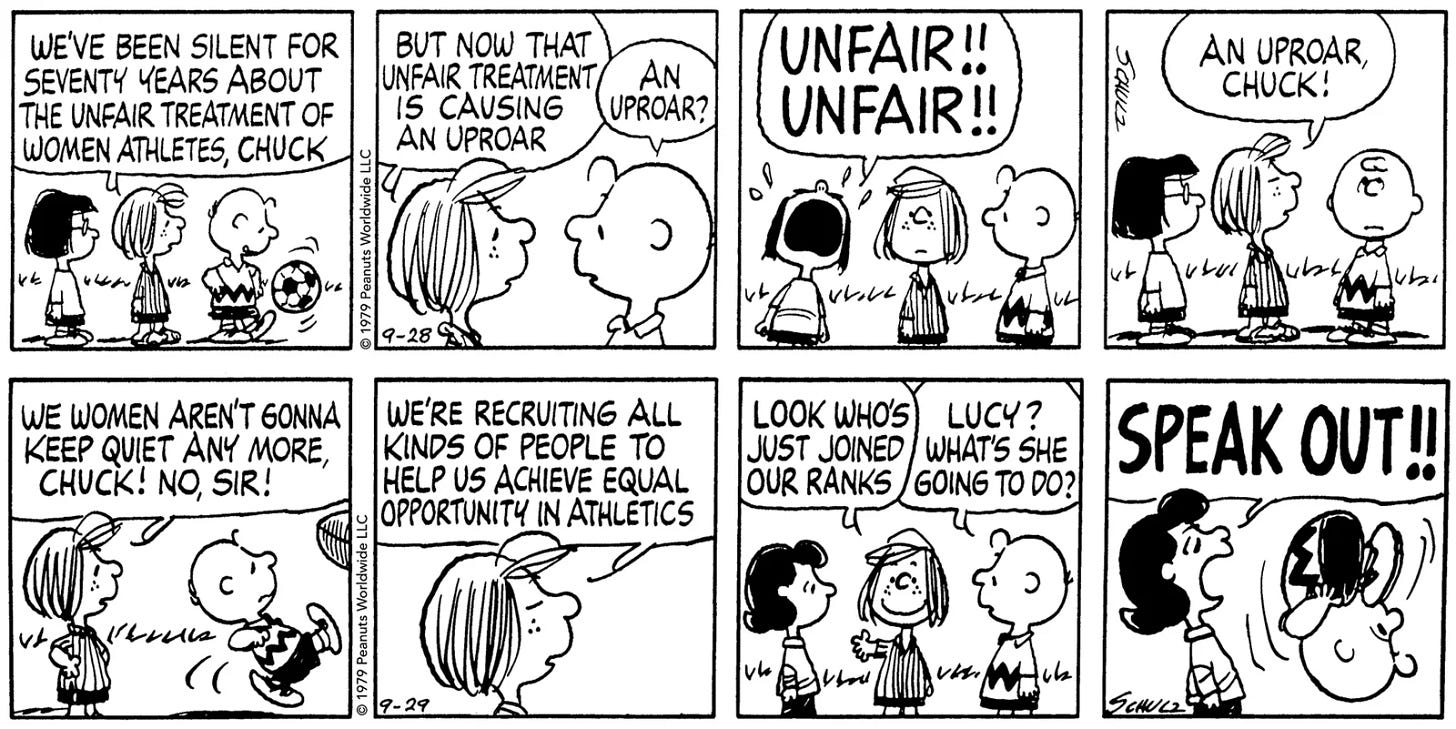
Tipo Aquilo #82 – Ziraldo e as letras dos quadrinhos
Analisando letras de quadrinhos e das artes de Ziraldo
Enquanto eu escrevo esse texto, há poucas horas, foi para as estrelas um dos mais ilustres cidadãos de Caratinga, MG. Aos 91 anos, Ziraldo faleceu em sua residência, deixando um legado de dezenas de personagens desenhados em milhares de quadrinhos, charges e cartuns. Eu sou da geração que conheceu a obra gráfica dele pelo Menino Maluquinho, sua peculiar panela na cabeça e sua turma que andava por jornais, gibis e chegou também aos cinemas. Mais ou menos na mesma época, conheci também o lado editorial de Ziraldo durante a breve existência da Bundas, uma sátira mensal da revista Caras criada para publicar entrevistas, artigos e charges que ilustravam o cotidiano social e político de um Brasil que deixara de ser uma ditadura de malditos milicos há pouco mais de 10 anos.
Como instrumento de crítica sócio-política pública, a Bundas não foi uma novidade na vida de Ziraldo; nos anos 1960, após passar por vários jornais de renome como cartunista, ele fundou “O Pasquim” com outros ilustradores da época, fazendo frente à gradual deterioração da democracia brasileira antes e após o golpe de 31 de março 1º de abril de 1964. O humor debochado era uma marca de Ziraldo, algo tão facilmente reconhecível quanto os traços de seus personagens e as letras espessas e cheias de contraste que escrevia para representar falas e outros elementos textuais. Aliás, é falando brevemente da história das letras usadas em quadrinhos que o Tipo Aquilo presta uma singela homenagem ao Ziraldo.
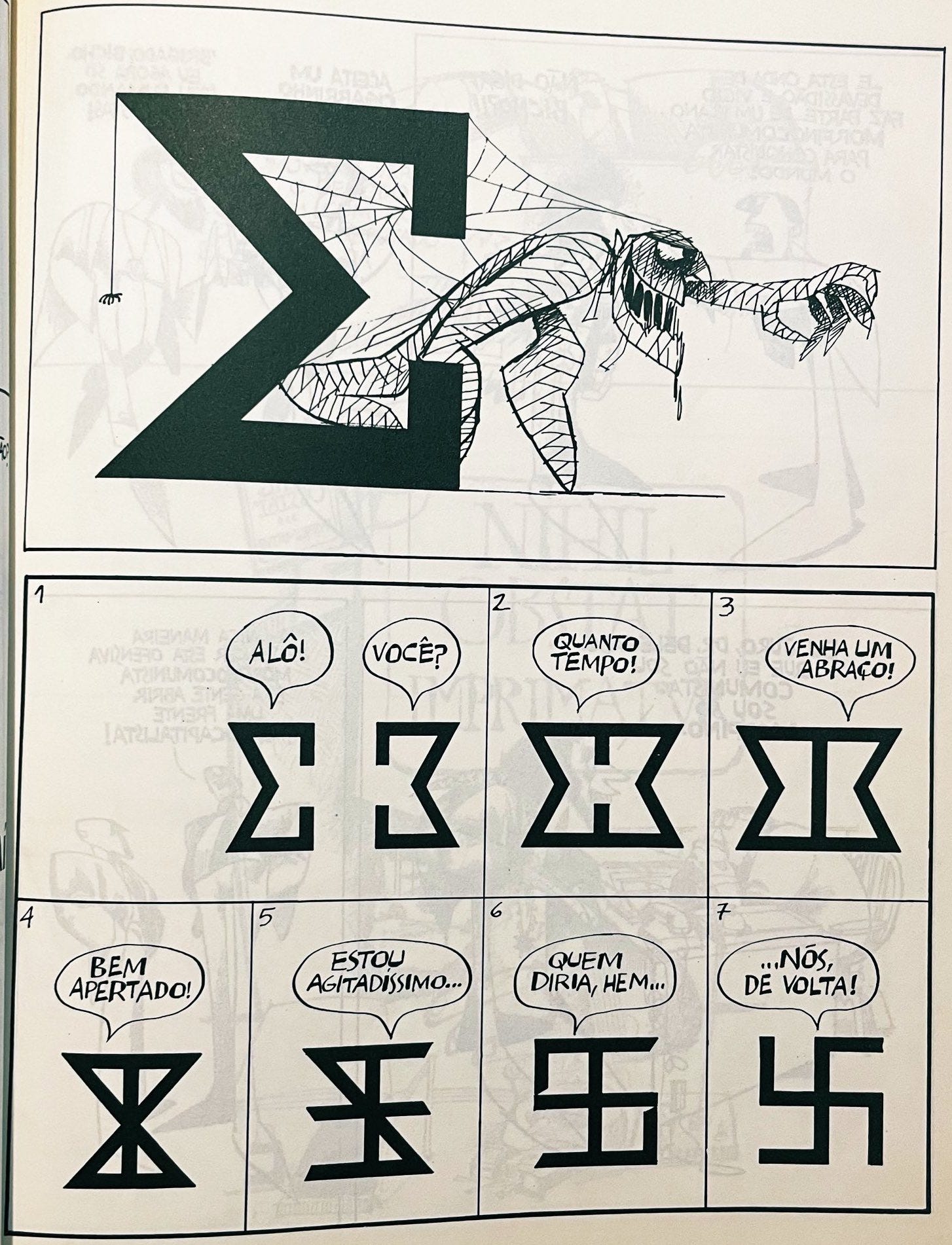
A história dos quadrinhos, por si só, é bastante profunda e renderia edições a perder de vista. Mesmo que a gente estabeleça a Action Comics #1, de julho de 1938, como um ponto inicial, a revista com primeira aparição do Superman é fruto de dezenas de anos de experimentação, tentativa e erro na narração de histórias em arte sequencial. Tirinhas e ilustrações impressas em jornais e disponíveis em bancas não eram mais novidade para o grande público. No entanto, a necessidade de imprimir em papel barato de má qualidade era algo em comum entre os recém-lançados gibis de heróis da Detective Comics e a arte sequencial de outros periódicos da época. Demoraria dezenas de anos até que quadrinhos virassem algo cult, que valesse a pena uma produção gráfica enobrecida. Dessa forma, desenhistas de personagens com ou sem superpoderes precisaram criar o superpoder de adaptar seus trabalhos às condições paupérrimas de impressão.
Conforme os quadrinhos tornaram-se um produto de sucesso comercial, produzi-los em escala exigiu separar entre artistas distintos os elementos fundamentais de uma história. A primeira, e mais óbvia, divisão foi entre quem desenha e quem escreve a narrativa, consolidando o formato de dupla ilustrador/escritor. Outras funções começaram a ser divididas também, criando profissionais como os coloristas, responsáveis por colorir e conferir noções de volume e perspectiva de acordo com o tom que o escritor deseja passar ao leitor. As letras também foram terceirizadas do trabalho do ilustrador, tornando-se objeto de trabalho dos letristas, responsáveis por criar e preencher balões de fala, complementar cenas de ação com onomatopeias, projetar layouts de capas e marcas das próprias revistas.
A presença do letrista na indústria de quadrinhos ajudou a criar um estilo de escrita de quadrinhos que tornou-se marcante no design gráfico. Feitas à mão para serem legíveis mesmo sob condições ruins de impressão, as letras eram majoritariamente maiúsculas, largas, com contraformas fartas e traços com gestualidade bem presente, distanciando-se das letras mecânicas das oficinas tipográficas. Era comum também o uso de negrito e itálico para dar ênfase a algumas partes importantes das falas, quando letristas usavam penas ou canetas técnicas mais espessas para dar efeito de negrito, e entortavam as letras em ângulos expressivos para reproduzir o efeito itálico. Algumas tentativas de mecanizar o processo de letreiramento das histórias em quadrinhos falharam em reproduzir essa gestualidade reconhecível de longe por outros artistas e os fãs dessa nova arte, garantindo a presença dos letristas na industria até os anos 1990. O desktop publishing, nesta década, tornou-se padrão para a criação de novas HQ's e o trabalho dos letristas foi substituído por fontes que replicavam com maior fidelidade o estilo clássico das letras feitas entre as décadas de 1930 a 1990.
O barateamento dos processos gráficos e o enobrecimento da produção das HQ's após a década de 1990 aprimorou a impressão dos gibis, permitindo o uso de tipografias em tamanhos pequenos e impossíveis de serem reproduzidos com nitidez no passado. Contudo, mesmo com essa melhoria na produção gráfica, o estilo de letra de quadrinhos vingou, sendo encontrado até hoje em qualquer revista de Marvel, DC ou quaisquer editoras de histórias em quadrinhos. Richard Starkings, letrista de quadrinhos famosos como “Batman: a Piada Mortal” e criador da foundry Comicraft, foi um dos responsáveis por essa transição que agilizou a produção de quadrinhos no ambiente digital. O uso dessas fontes virou também um cliché do design gráfico para emular a linguagem dos quadrinhos nas narrativas presentes em quaisquer peças gráficas e até em outras mídias, como na TV e no cinema.
Entre os artistas independentes de arte sequencial, a coisa muda de figura. Sendo responsáveis por quase tudo na produção de suas obras, as letras dos quadrinistas indies torna-se uma marca registrada do artista, complementando seu traço e a forma com que dispõe elementos visuais ao longo de suas páginas. Também, entre os quadrinistas independentes, é comum o uso exclusivo de letras maiúsculas, mais fáceis de serem escritas com uniformidade e que aproveitam melhor o pouco espaço disponível dentro do quadro e do balão de fala. Tendo que cuidar de história, roteiro, desenho, letreiramento e cores, as falas e elementos textuais ao longo da publicação não têm o mesmo apuro que os quadrinhos das grandes editoras, uma diferença que colabora para afastar o fã de quadrinhos mainstream do circuito independente.
Com a tipografia digital, alguns artistas independentes conseguem reproduzir a própria escrita em fonte para agilizar a produção de novas páginas sem perder tanto sua autenticidade. A forma com que os elementos textuais e os traços de grandes quadrinistas se complementam é algo que permite a um verdadeiro entusiasta de HQ's reconhecer o autor apenas com algumas letras e entendê-las como uma parte indissociável da obra. Cartunistas como Charles Schultz, Bill Watterson, Robert Crumb, Art Spiegelman, Angeli, Laerte, Henfil, Adão Iturrusgarai, Glauco, Fernando Gonsales, Maurício de Sousa e Ziraldo são facilmente reconhecíveis pelas letras de suas tirinhas, charges e HQ's, que ornam com os traços de seus personagens e a forma com que texto e forma interagem ao longo das obras.
Contraste é um elemento constante nas letras que Ziraldo escreveu. Nos quadrinhos e tirinhas, nota-se leves diferenças entre alguns traços mais finos e espessos das letras em balões de fala. Nas charges, o desenho das letras torna-se ainda mais particular de Ziraldo, com as notórias contraformas quadradas interagindo com formas redondas e dando origem a formas de letras que conversam com curvas e retas presentes na anatomia de seus personagens. A disposição variada das letras, sem uma linha de base clara e com variações evidentes de largura e espessura de traços, também ajudava seu texto a ter o ritmo, a descontração e a irreverência necessária para entender a forma debochada com que Ziraldo via e representava o mundo. Essas letras também eram comuns nos títulos de capas de gibis, com efeitos de cor e sombra comuns na indústria. Essa autenticidade das letras do Ziraldo é algo digno de grandes artistas; no que toca meu lado tipográfico, nenhuma fonte é capaz de reproduzir no todo.
Aliás, Ziraldo é um personagem notório não só nos quadrinhos, mas também no design gráfico brasileiro, tendo produzido cartazes, alfabetos, marcas e ilustrações para livros e álbuns famosos. Ziraldo inspirou uma geração de cartunistas e defensores da democracia no Brasil, encantando crianças com as histórias do Menino Maluquinho e do Pererê, ensinando a fina arte de amar e valorizar a cultura brasileira, e mostrando a importância da consciência política e social para quem deseja um país melhor para todos. Ziraldo fez tanta coisa diferente que nem parece que até as suas obras mais singelas têm a cara dele, e isso é uma rara qualidade de quem sabe ser e mostrar-se autêntico. Se existe algo essencial de aprender com Ziraldo, mais do que saber desenhar ou criar histórias, é essa arte da autenticidade.
🎥 Vídeo: Where the "comic book font" came from, (em inglês) um vídeo da Vox mostrando a origem e história do estilo de letras de quadrinhos.
🇧🇷 Fonte brazuca: Mudstone, de Erica Jung e Ricardo Marcin.